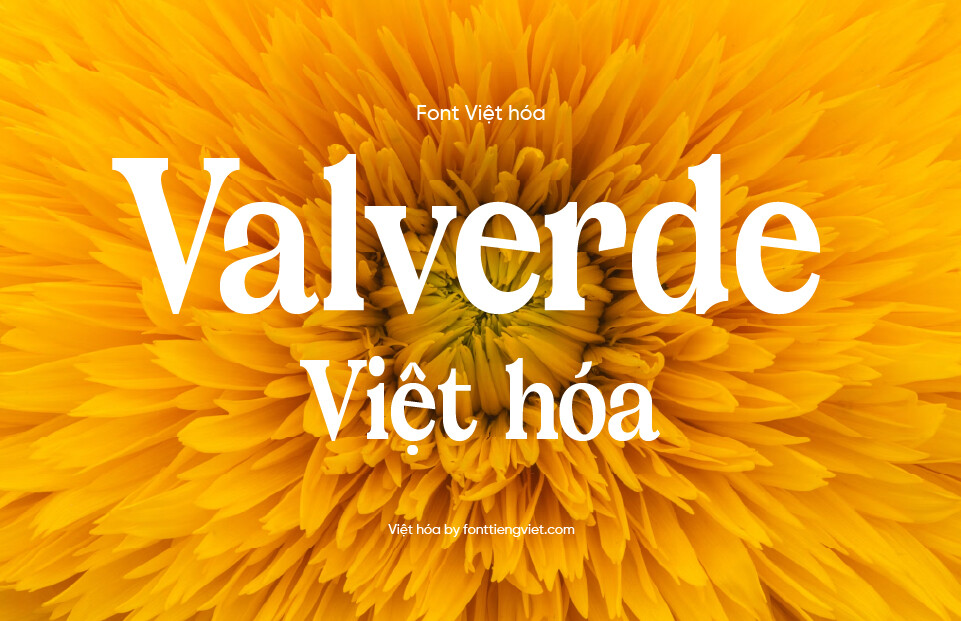
Font Việt hóa 1FTV VIP Valverde
Giới thiệu về Font Việt hóa 1FTV VIP Valverde
Trong thế giới đồ họa hiện đại, việc tìm kiếm một bộ Font Miễn Phí chất lượng cao là ưu tiên hàng đầu của các nhà thiết kế. Font Việt hóa 1FTV VIP Valverde nổi lên như một hiện tượng nhờ sự kết hợp hoàn hảo giữa nét cổ điển serif và tư duy thẩm mỹ đương đại. Đây không chỉ là một phông chữ thông thường mà còn là công cụ đắc lực giúp nâng tầm giá trị cho các bản thiết kế từ sách báo, tạp chí đến các ấn phẩm truyền thông học đường. Bộ font này đặc biệt được ưa chuộng bởi tính ứng dụng cao và sự chỉn chu trong từng đường nét ký tự đã được căn chỉnh tỉ mỉ theo bảng mã tiếng Việt chuẩn.
Đặc điểm nổi bật của Font Việt hóa 1FTV VIP Valverde
Thiết kế Serif tinh tế và đẳng cấp
Điểm mạnh nhất của Font Việt hóa 1FTV VIP Valverde chính là các đường chân (serif) sắc sảo nhưng không quá cứng nhắc. Các nhà thiết kế đã tạo ra sự tương phản nhẹ nhàng giữa các nét thanh và nét đậm, mang lại cảm giác dễ đọc nhưng vẫn đầy tính nghệ thuật. Đối với các bạn học sinh hay thầy cô giáo đang thực hiện các bài thuyết trình, bộ font này giúp nội dung trở nên chuyên nghiệp và trang trọng hơn rất nhiều. Khả năng hiển thị tốt trên cả màn hình kỹ thuật số và giấy in giúp nó trở thành lựa chọn hàng đầu cho các dự án in ấn chất lượng cao.
Hỗ trợ tiếng Việt hoàn chỉnh và đa dụng
Một rào cản lớn khi sử dụng font nước ngoài là lỗi dấu tiếng Việt. Tuy nhiên, với phiên bản Font Việt hóa 1FTV VIP Valverde, toàn bộ các ký tự đặc biệt và dấu câu đã được xử lý mượt mà. Người dùng sẽ không còn gặp phải tình trạng lỗi font hay mất chữ khi soạn thảo văn bản. Điều này cực kỳ quan trọng trong môi trường giáo dục, nơi sự chính xác về mặt ngôn ngữ luôn được đặt lên hàng đầu. Bạn có thể tự tin sử dụng font này cho các tiêu đề lớn hoặc thậm chí là các đoạn văn bản dài mà vẫn đảm bảo được sự thống nhất về thẩm mỹ.
Ứng dụng thực tế trong thiết kế và học tập
Sáng tạo ấn phẩm truyền thông học đường
Font Việt hóa 1FTV VIP Valverde cực kỳ phù hợp để thiết kế bìa sách, poster sự kiện trường học hoặc các mẫu chứng nhận khen thưởng. Sự sang trọng của font chữ này tạo nên sự tin cậy và nghiêm túc, rất thích hợp cho các bối cảnh sư phạm. Ngoài ra, các bạn sinh viên ngành mỹ thuật có thể sử dụng nó trong các đồ án nhận diện thương hiệu để tạo ra điểm nhấn khác biệt. Không cần quá cầu kỳ, chỉ cần sử dụng bộ font này là tác phẩm của bạn đã sở hữu một diện mạo hoàn toàn mới, thanh lịch và thu hút người xem từ cái nhìn đầu tiên.
Kết luận về bộ font chữ độc đáo